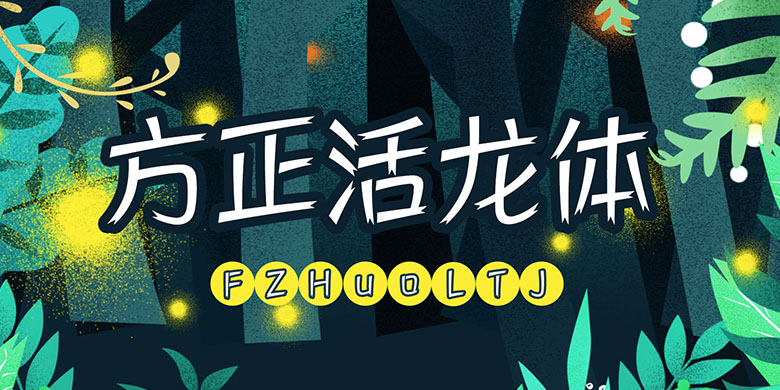
方正活龙体-简繁-ExtraLight
活龙体:郭老师有一次去香港新界一家礼品包装公司参观,看见许多工人用丝带包装礼物,同时拍摄了一条像龙一样的丝带,尾部开了叉口,于是灵感又来了,然后研发了“活龙体”,它的特点是横,直划粗细平均,所有笔划头部斜直而末端开了叉口,而且点,撇,捺,抅等都是弧形,没有垂直平行线的,横划重心向右上方斜上,让它活一些,有动感和速度,像一条龙在天空飞舞,测试制成全款字体后,效果好理想,符合郭老师的要求,它含8种粗细,每种粗细都活力十足,是一款崇高价值的创意字体,希望同胞们鼎力支持,它最适合体育用品名牌,年青人生龙活虎的饮料,舞蹈培训宣传,男士健康食品广告,药物广告宣传和包装设计等。